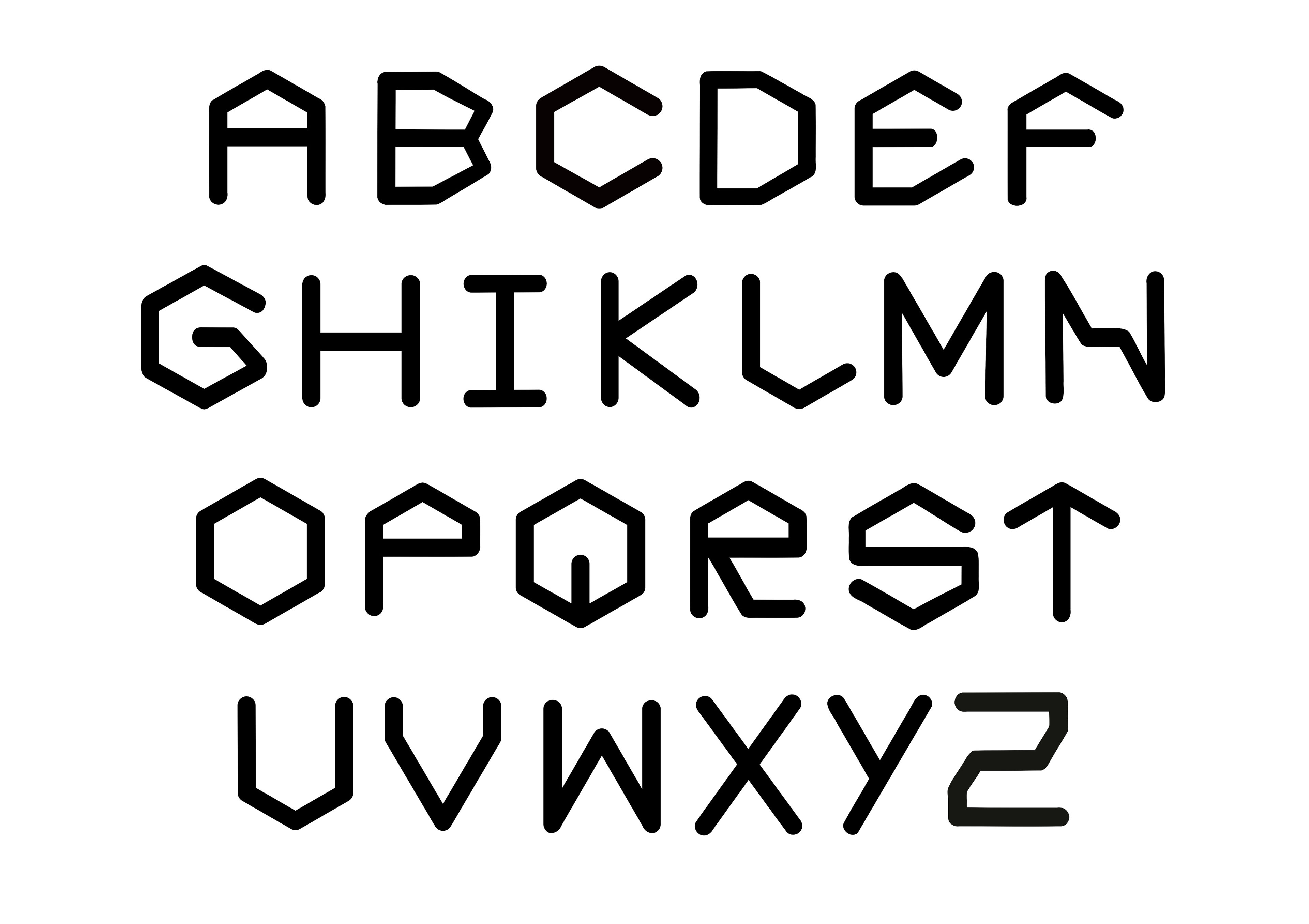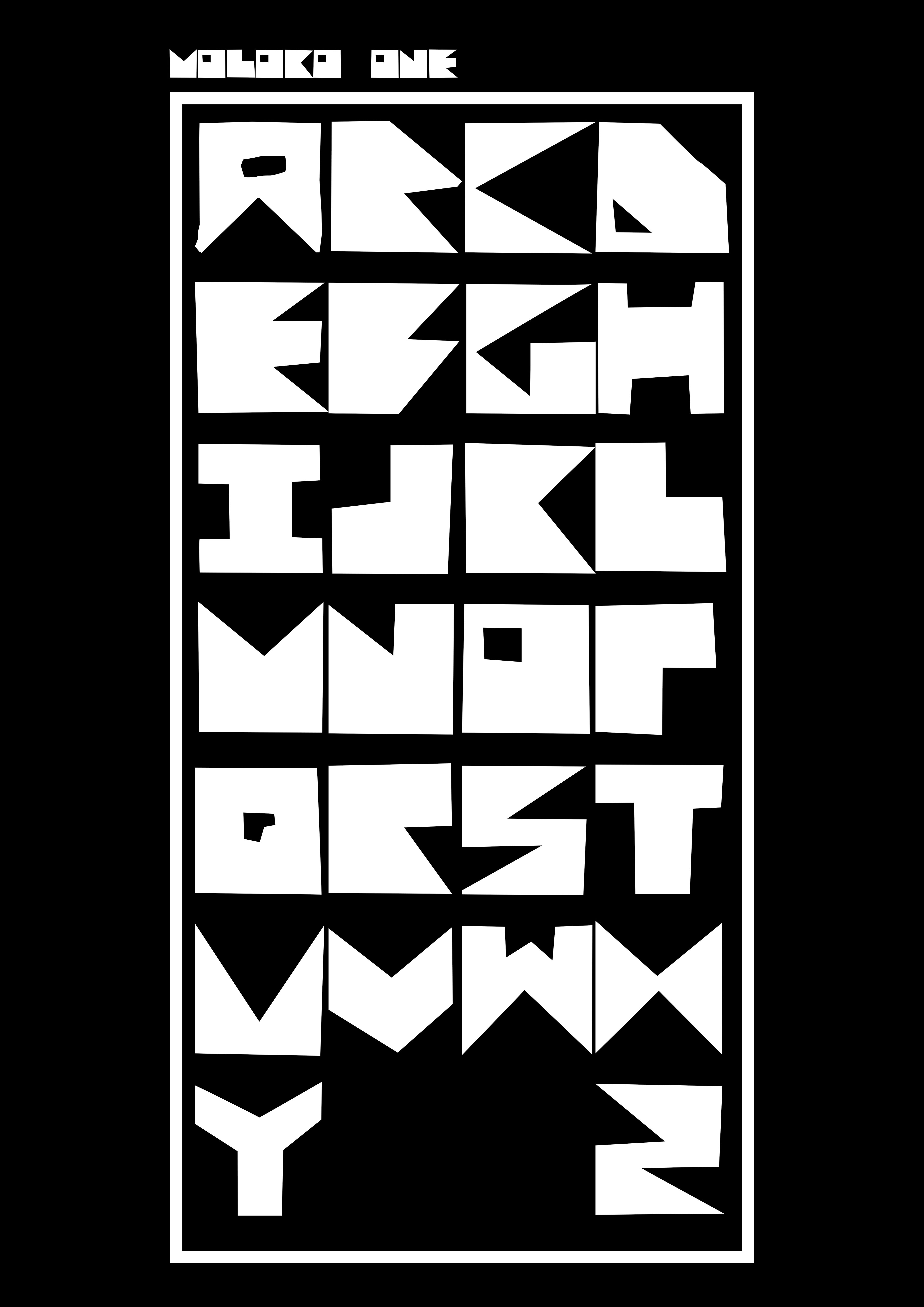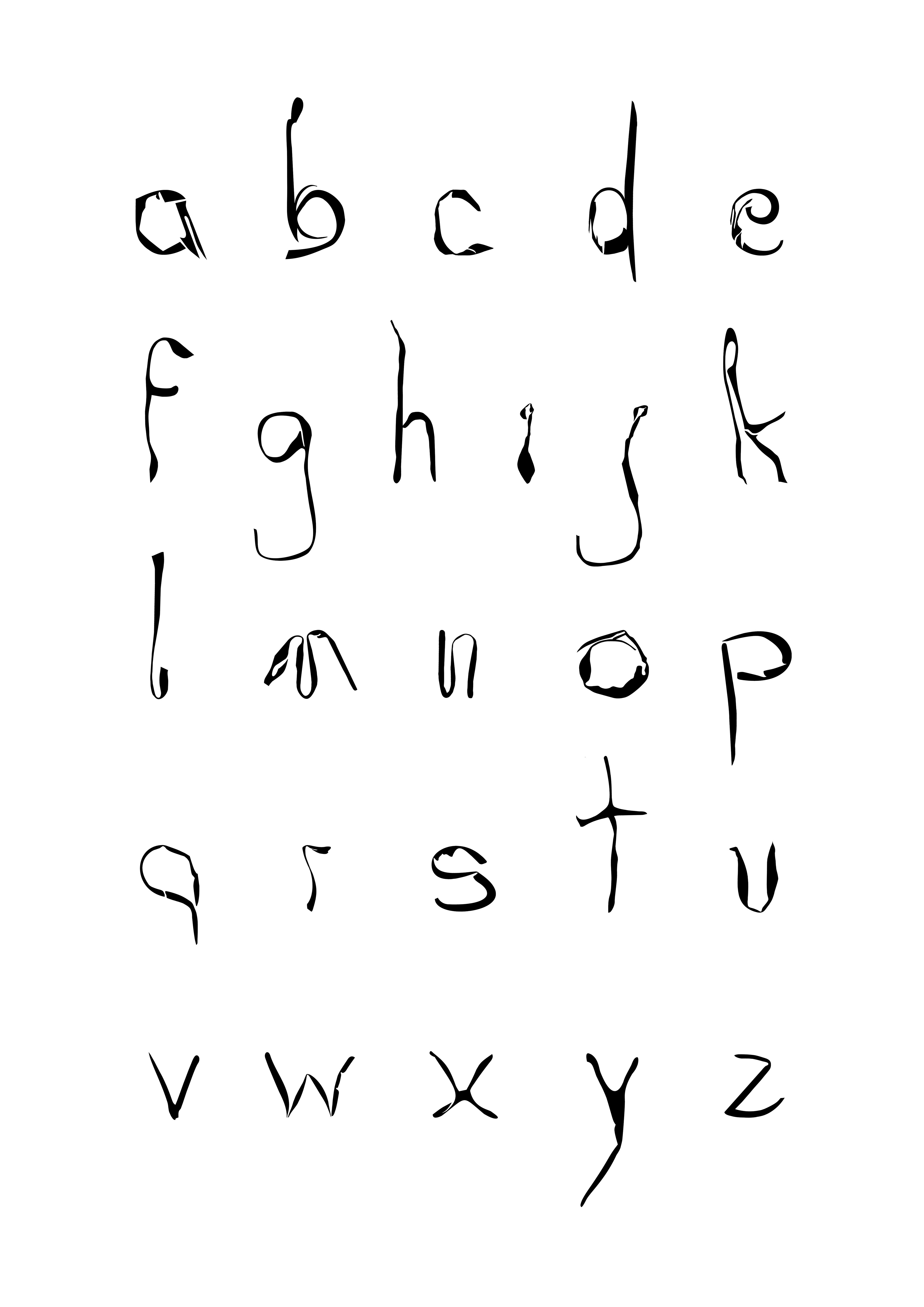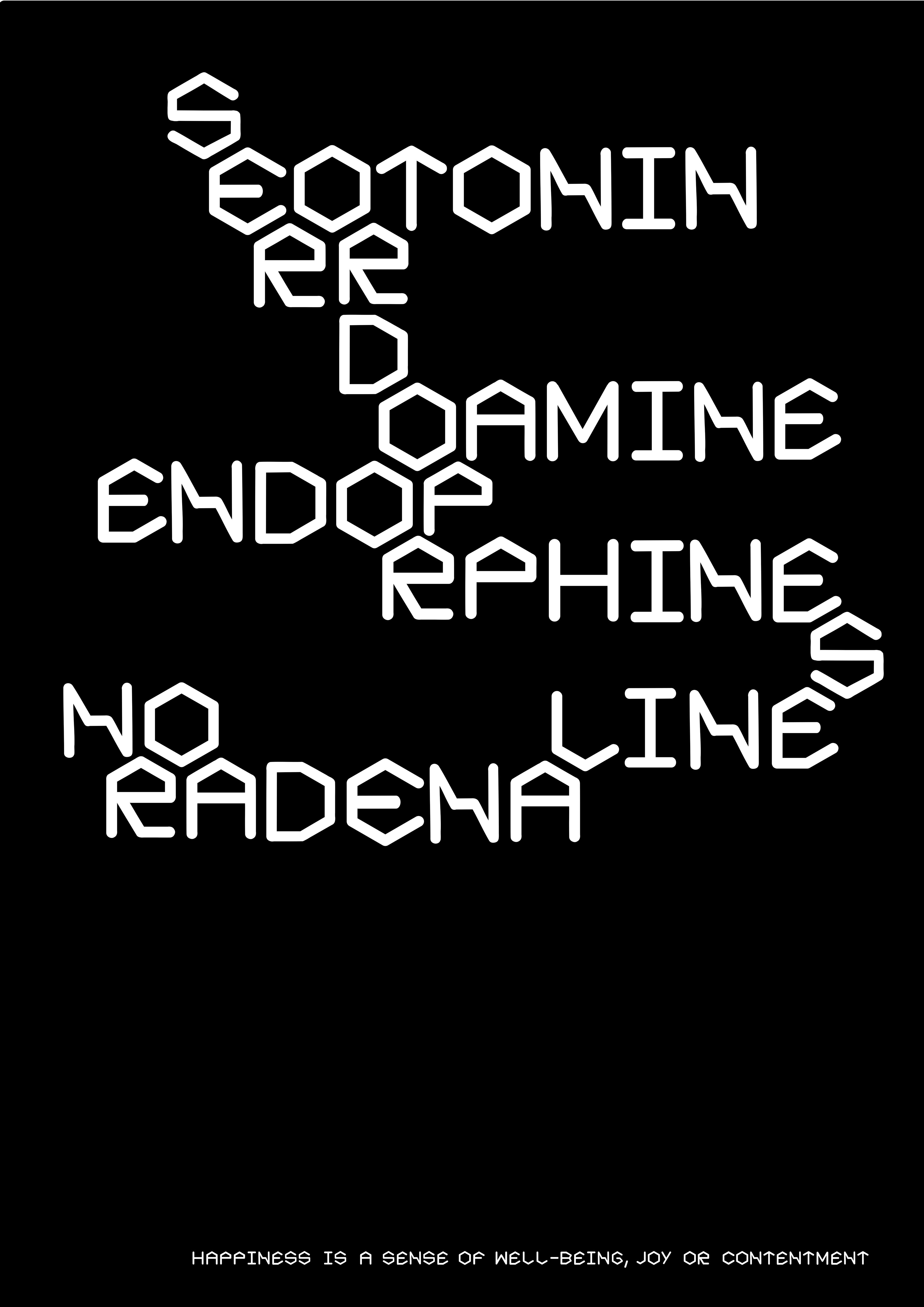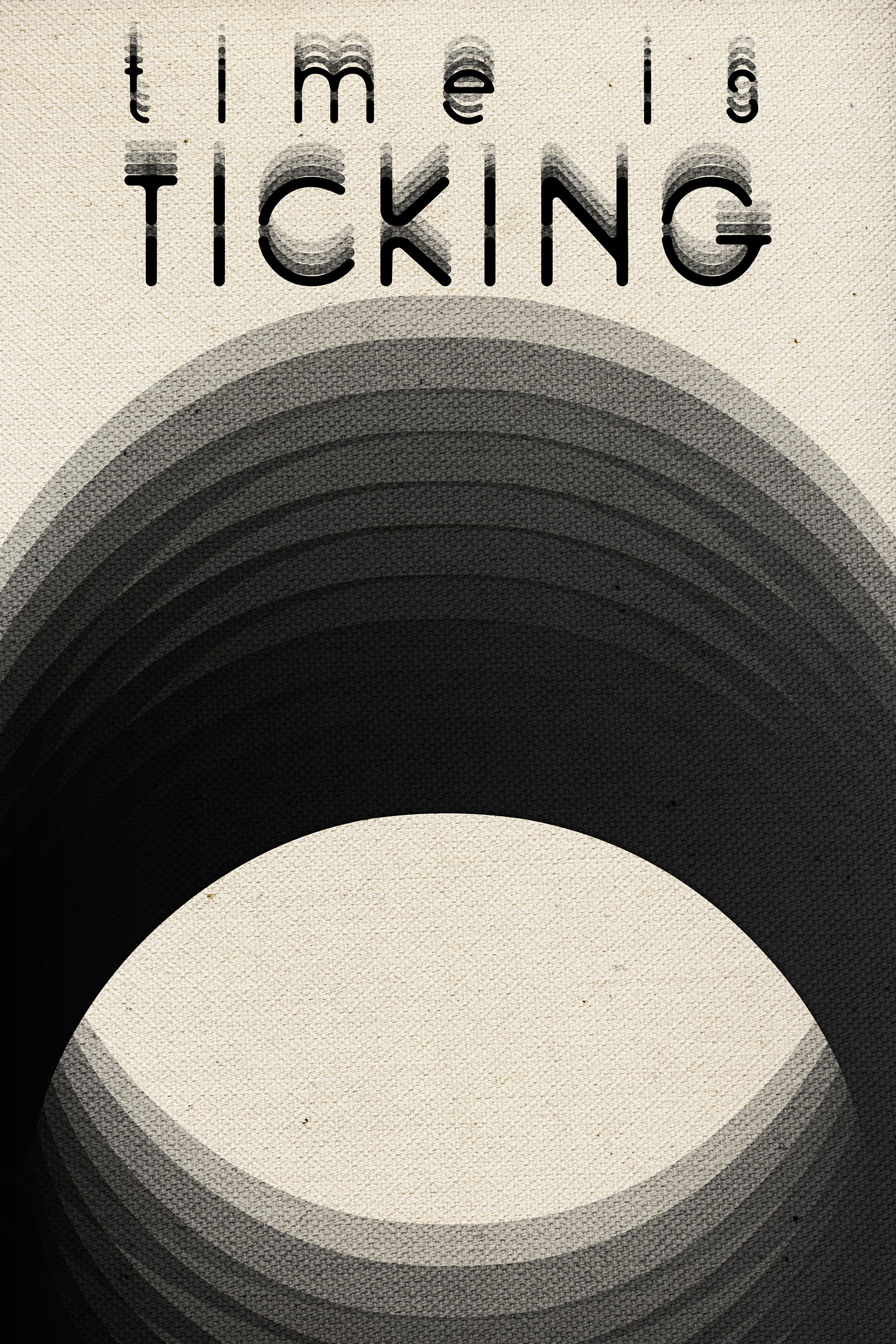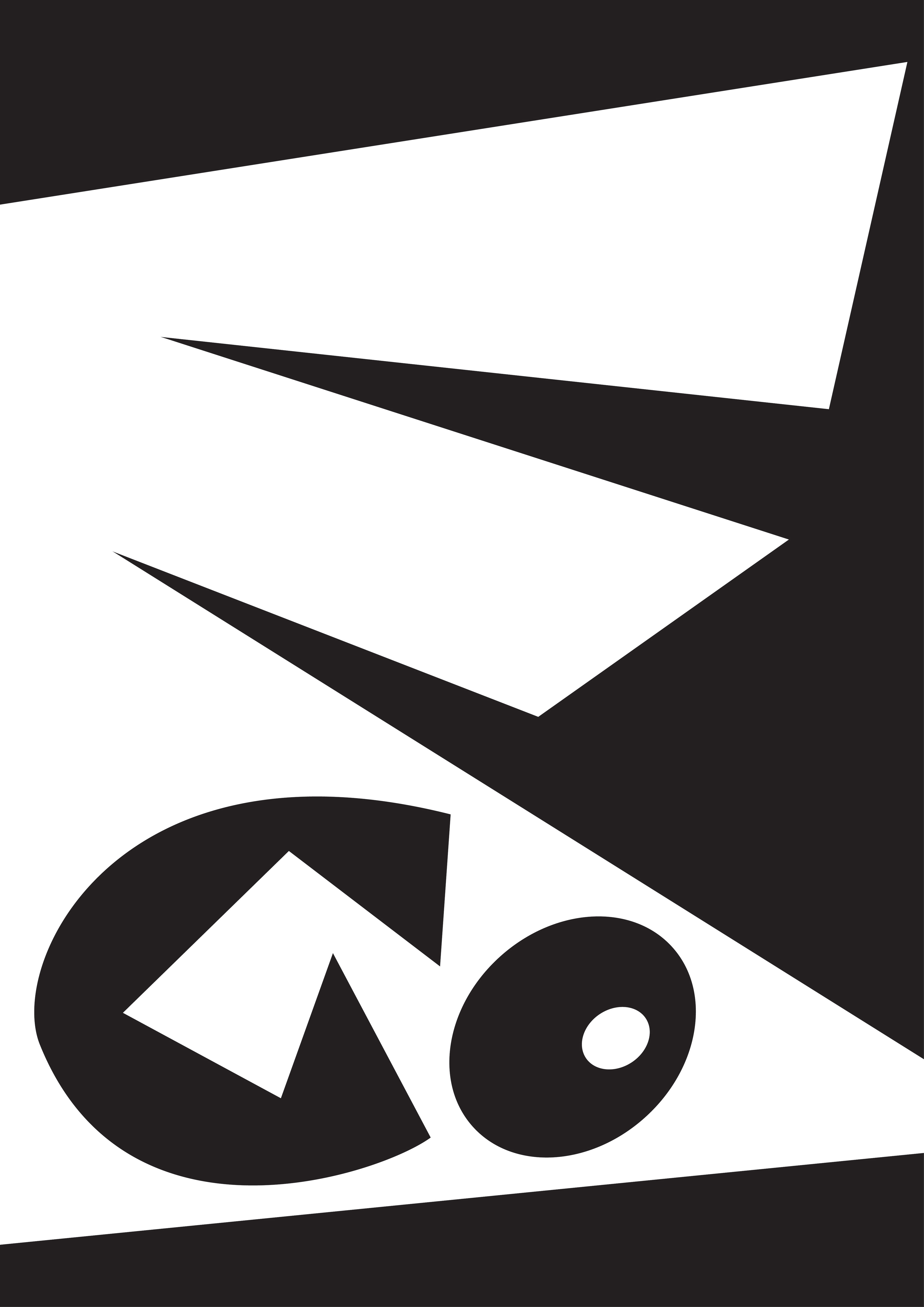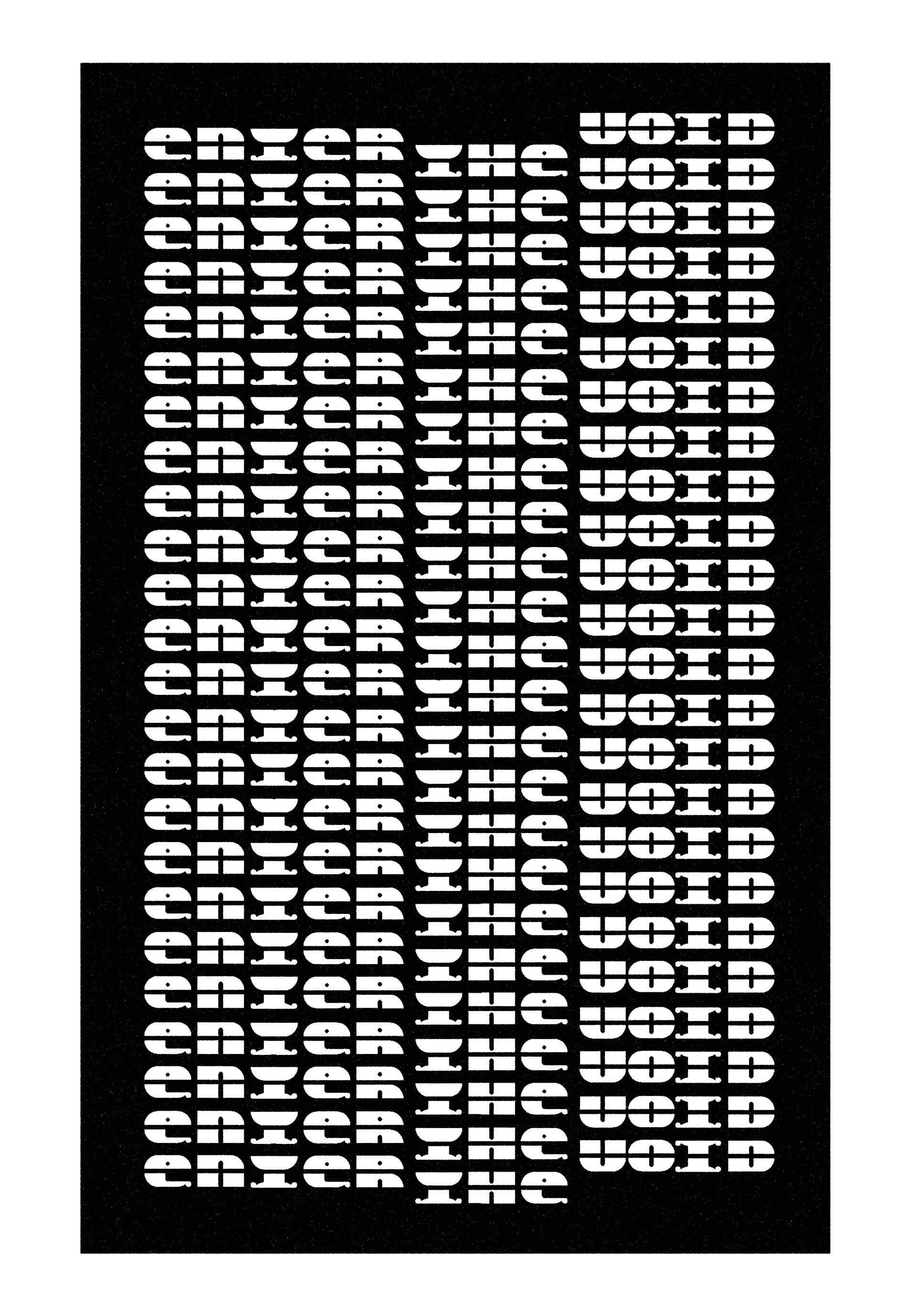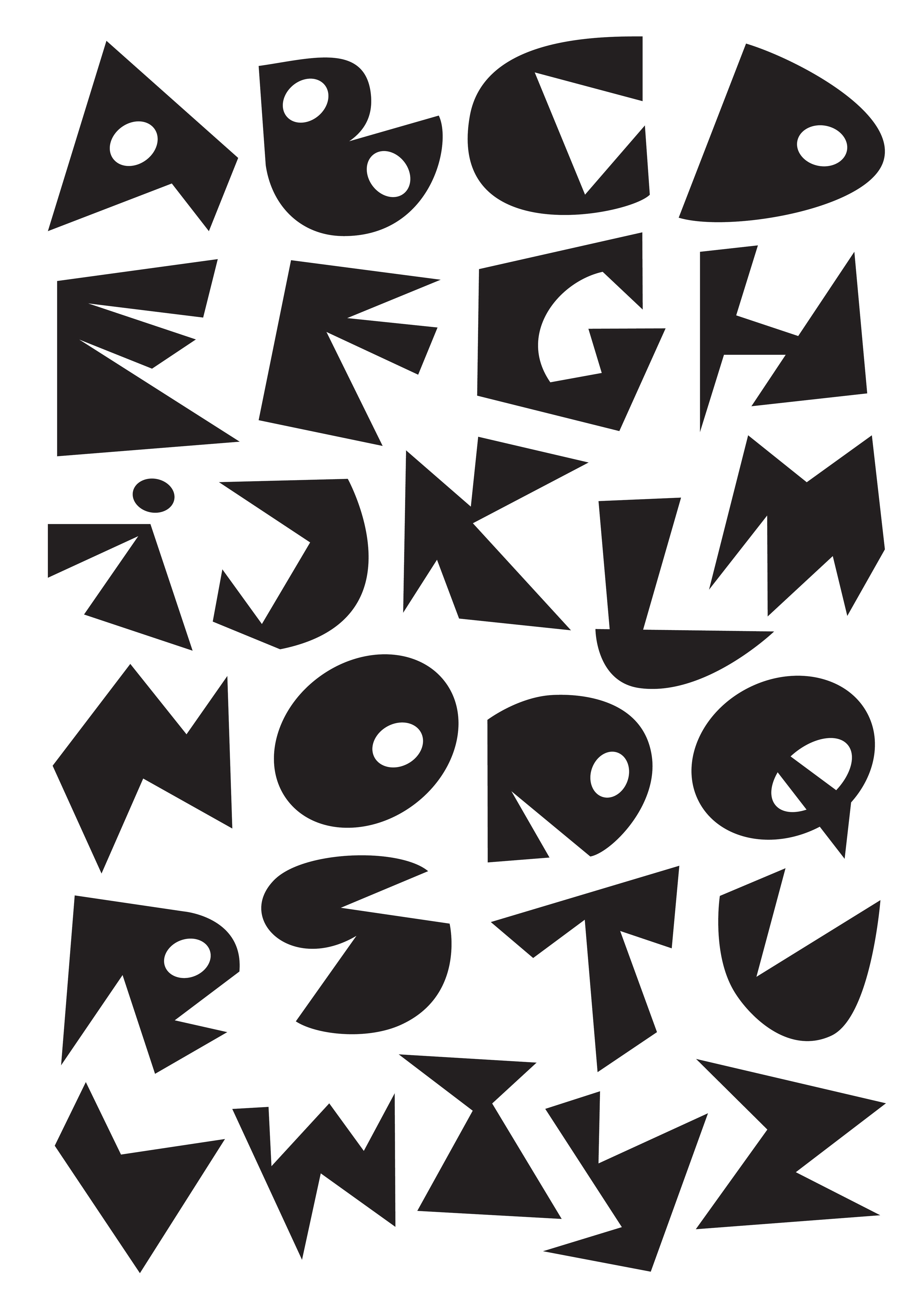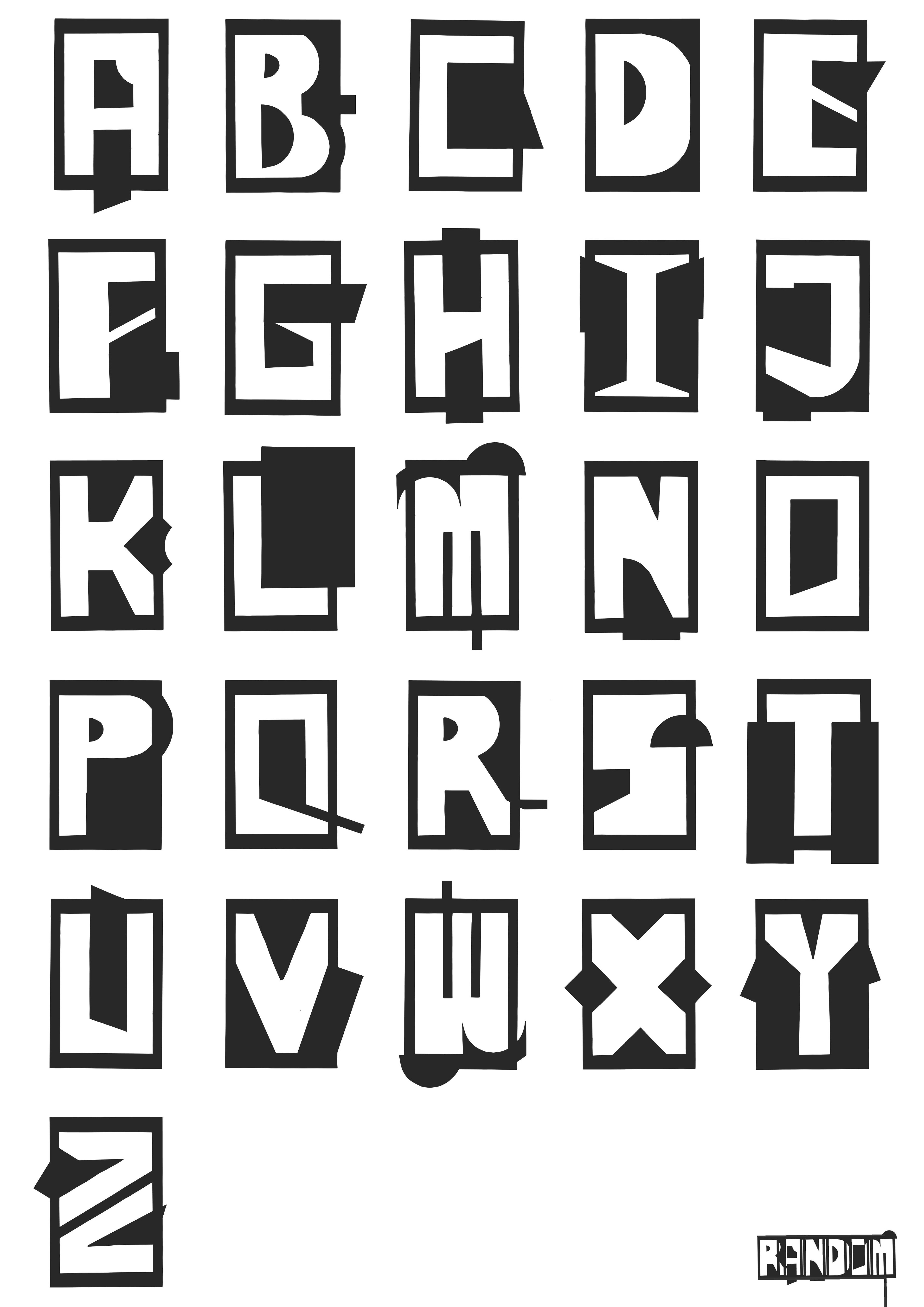
_Am Anfang stand das Wort. Irgendwann kam die Schrift. Und irgendwann kamen die Dreißiger. Das historische Bauhaus gilt als Meilenstein der Sans-Serif. EinBlick 20/21 stellte im Bereich Typografie die Aufgabe, eigene Typefaces nach Baukastensystem in Anlehnung an die Weimarer Urahnen zu entwickeln und diese in Form von beispielhaften Mottos zum Modulthema zu inszenieren.
_At the beginning, there was language. Sometime later, scripture came along. And eventually, the thirties arrived. The historic Bauhaus is seen as a mile stone of the sans serif. EinBlick 20/21 instructed the students to design their own fonts (following the ancestors of Weimar) and to present those in the form of posters with exemplary statements.